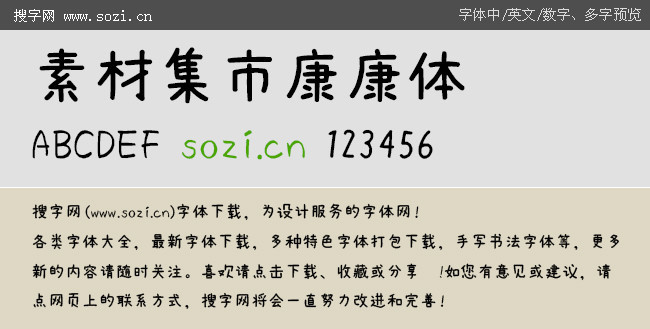
素材集市康康體
搜字網(wǎng)提供一款免費(fèi)可商用的素材集市康康體中文字體下載,素材集市康康體是一款萌系可愛(ài)手寫風(fēng)格中文字體,字庫(kù)共 2623 個(gè)漢字和字符,能夠滿足正常書寫使用。提供給大家免費(fèi)商用。適合兒童包裝設(shè)計(jì),網(wǎng)頁(yè)設(shè)計(jì),海報(bào)設(shè)計(jì)等場(chǎng)合使用。